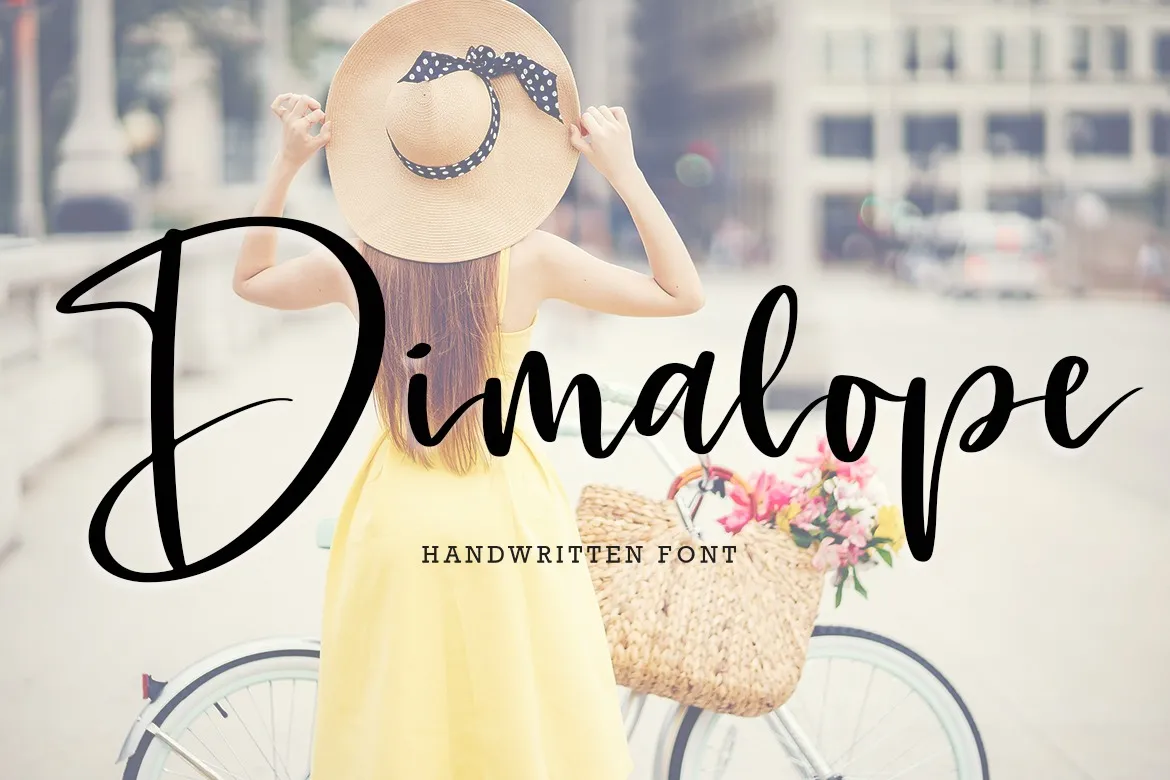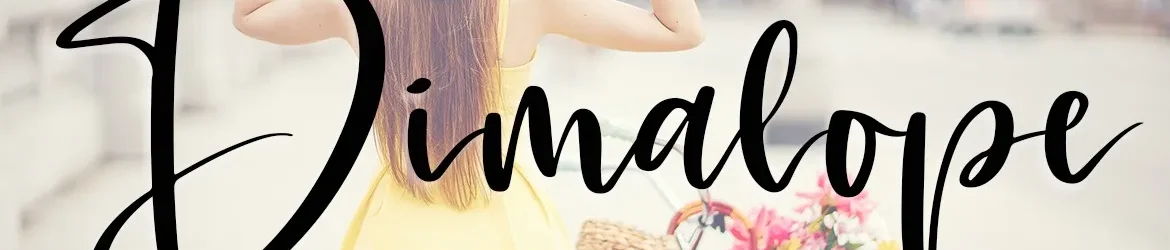
Dimalope Font – Download Grátis
A Dimalope Font é uma fonte script romântica e delicada criada por Lyanatha, com caracteres que dançam sobre a linha base. Ela oferece um toque personalizado ideal para estilos gráficos como convites de casamento, cartões de agradecimento, frases motivacionais, cartões de cumprimentos, logotipos e cartões de visita. Esta fonte traz uma sensação encantadora às criações, tornando-as ideais não apenas para o ambiente formal das festas de casamento, mas também para qualquer design que deseje um toque de autêntica escrita a mão. Perfecto para designers gráficos em busca de uma adição sofisticada e romântica a seus projetos, a Dimalope Font é certamente algo a ser considerado no seu portfólio.